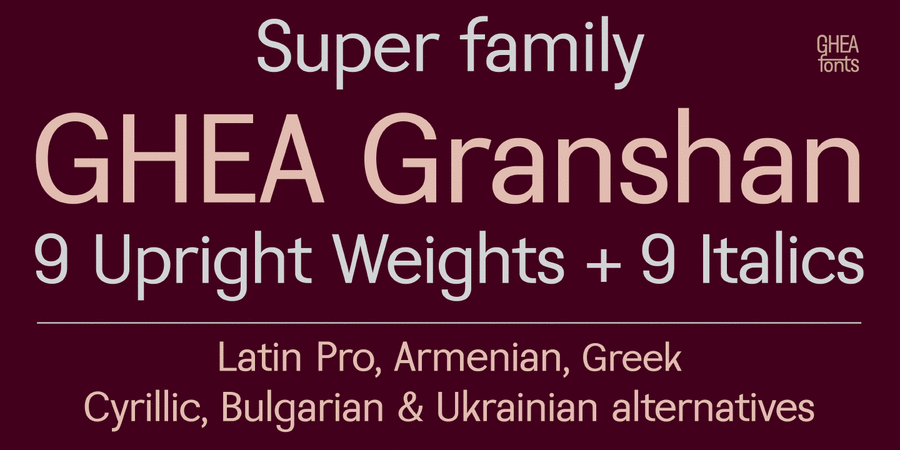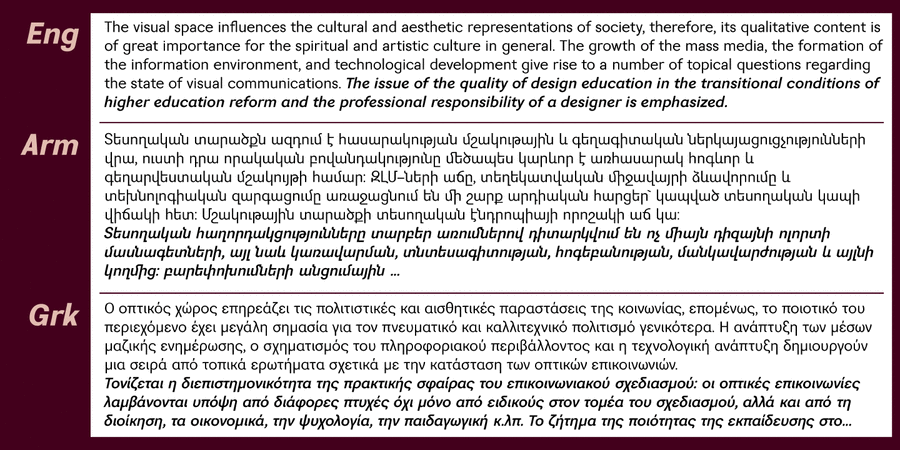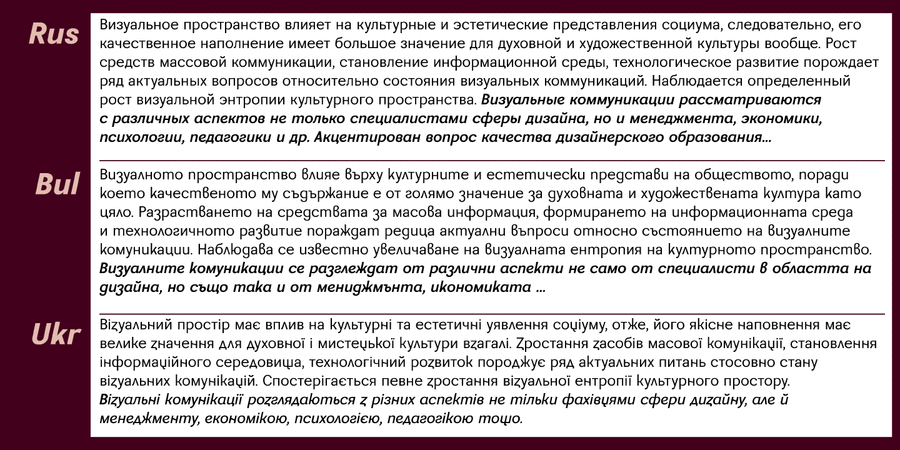
Це суперсімейство має 9 прямих і 9 курсивних накреслень. Шрифт підтримує латинку, вірменську та грецьку абетки, кирилицю, а також альтернативні знаки для болгарської та української кирилиці. У якості текстових шрифтів можна використовувати накреслення від Regular до Bold і їх курсиви. Для акциденції можна використовувати світліші, ніж Regular та жирніші, ніж Bold. Цей шрифт легко читається, очі не втомлюються. GHEA Granshan має легкий контраст, але в той же час, він досить яскравий та простий. Шрифт розробив Едік Габузян у 2021 році.
Особливості сімейства шрифтів GHEA GranshanХіт десятиліття:
Хіт 1960-х GHEA Granshan підтримує 86 мовУкраїнська, Англійська, Німецька, Польська, Португальська, Іспанська, Вірменська, Французька, Грецька (сучасна), Російська, Чеська, Голландська, Італійська, Шведська, Турецька, Фінська, Білоруська, Грецька, Сербська, Болгарська, Естонська, Литовська, Албанська, Африкаанс, Баскська, Бретонська, Валенсаска, Galician, Гельська (Шотландська), Данська, Індонезійська, Ірландська, Ісландська (Win), Каракалпацька, Каталонська, Норвезька, Окситанська, Ретороманська, Самі Лулі, Тсванська, Узбецька (Лат.), Фарерська, фризька, Чаморро, Естонська (Win), Південносаамська, Албанська (Win), Угорська, Верхньолужицька, Карельська, Латвійська (Mac), Литовська (Mac), Маорійські (Mac), Молдавська (Лат.), Нижньолужицька, Румунська (Win), Словацька, Словенська, Туркменська (Лат.), Хорватська (Win), Естонська (Mac), Курдська, Латишська, Маорійські, Руминська, Абазинська, Аварська, Агульська, Адигейська, Даргинську, Інгуську, Кабардино-Черкеська, Кабардинська, Карачаєво-Балкарська, Кумицька, Лакська, Лезгинська, Македонську, Мордовсько-Мокшанська, Мордовсько-Ерзянська, Ногайська, Рутульська, Табасаранська, Татська, Цахурська, Чеченська Функції сімейства шрифтів GHEA GranshanЗастосування гарнітури у верстці:
Асоціації з сімейством шрифтів GHEA GranshanОсобистість і характер гарнітури:
мінімалістичний, чіткий, делікатний, чистий, легкий, прохолодний, свіжий, тонкий, лаконічний, ясний, рівний, міський, точний, глобалізований, глобалістічний, скляний, крихкий, холодний, статичний, худий, якісний, Простий, твердий, зрозумілий, доступний, елементарний, правильний, формальний, серйозний, стійкий, стабільний, самостійний, відповідальний, діловий, спокійний, нейтральний, помірний, стандартний, невиразний, універсальний, розумний, байдужий, непомітний, значний, обов'язковий, солідний, сильний, важкий, переконливий, важливий, урбаністичний, надійний, залізний, сталевий, грубий, впевнений, потужний, строковий, наполегливий, мужній, різкий, робочий, промисловий, суворий, технічний, індустріальний, яскравий, помітний, щільний, активний, машинний, техногенний, тісний
парфумерія, туалетна вода, шампунь, косметика, мода, Місто, інновації, дієта, гігієна, чистота, прилад, суспільство, наука, одяг, реклама, магазин, медицина, взуття, інженер, математика, ліки, бізнес, торгівля, гроші, коворкінг, освіта, техніка, рентген, хімія, фізика, монета, інструмент, верстат, урбаністика, паливо, енергетика, Зубна паста, сталевар, новини, автобус, мотор, двигун, технології, аптека, вантажівка, далекобійник, промисловість, будівництво, машинобудування, охорона, тренажери, електростанція, завод, цегла, порт, сейф, ремонт, захист, екскаватор, робочий Гарнітура має ознаки стилів: